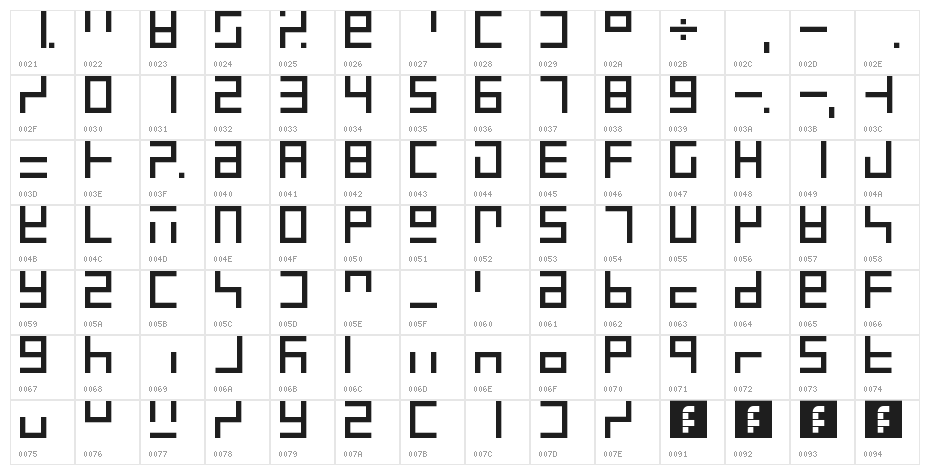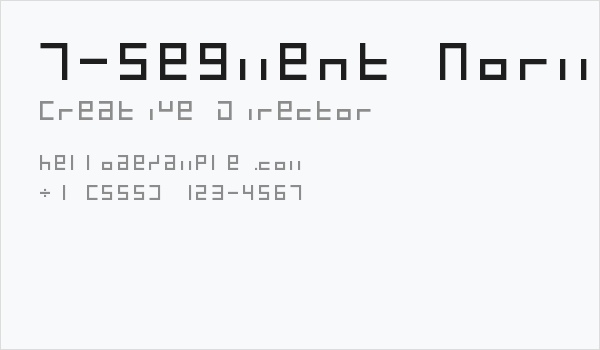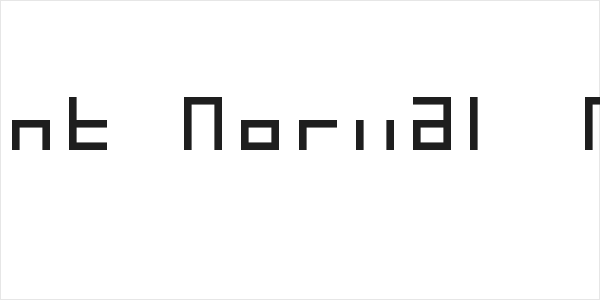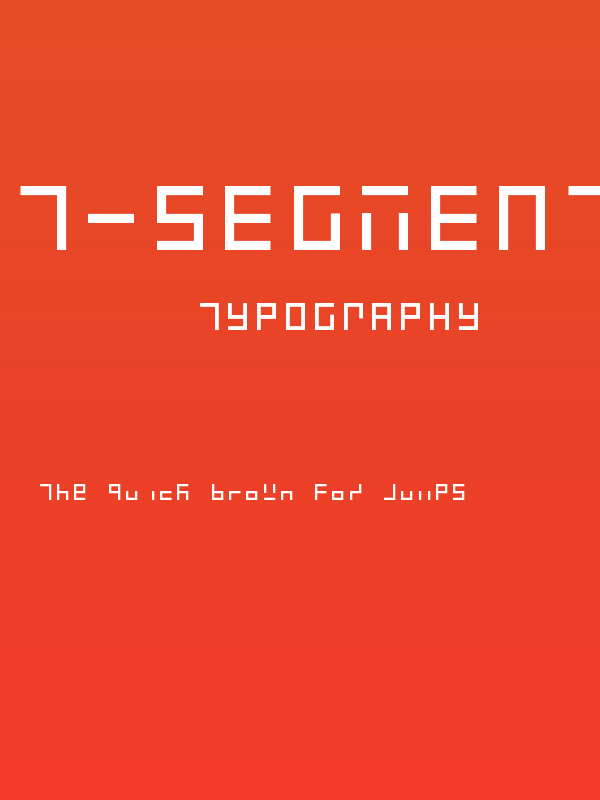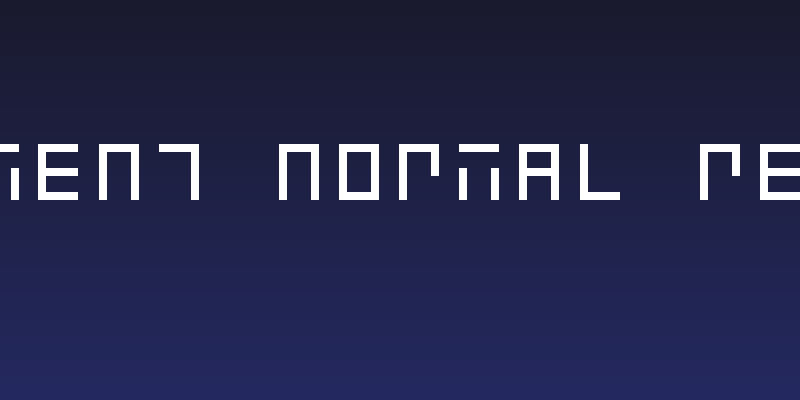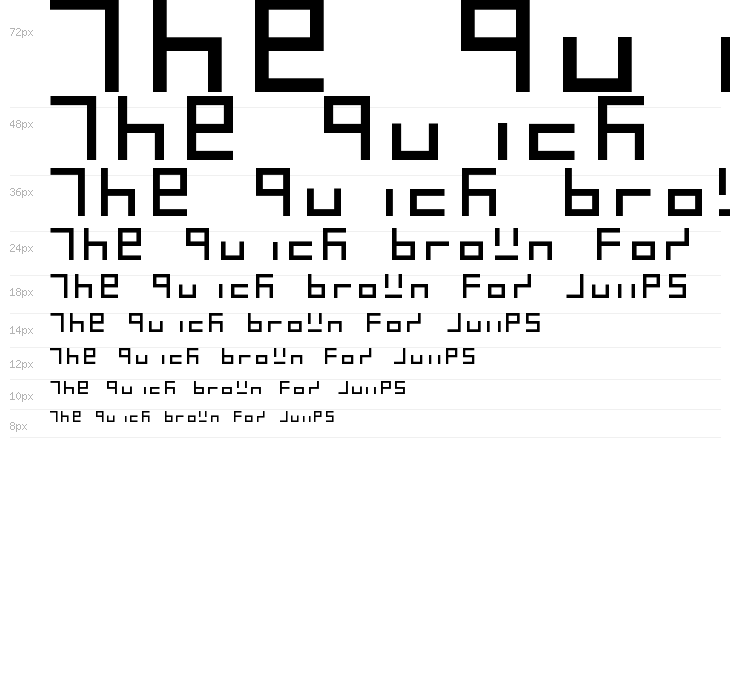
7-Segment Normal Regular Font
| Stile generale | Futuristic |
| Caso d'uso | Digital displays, tech interfaces, retro designs. |
| Progetti proposti | Ideal for digital interfaces, tech-themed designs, retro-futuristic projects, and any application requiring a digital or electronic aesthetic. |